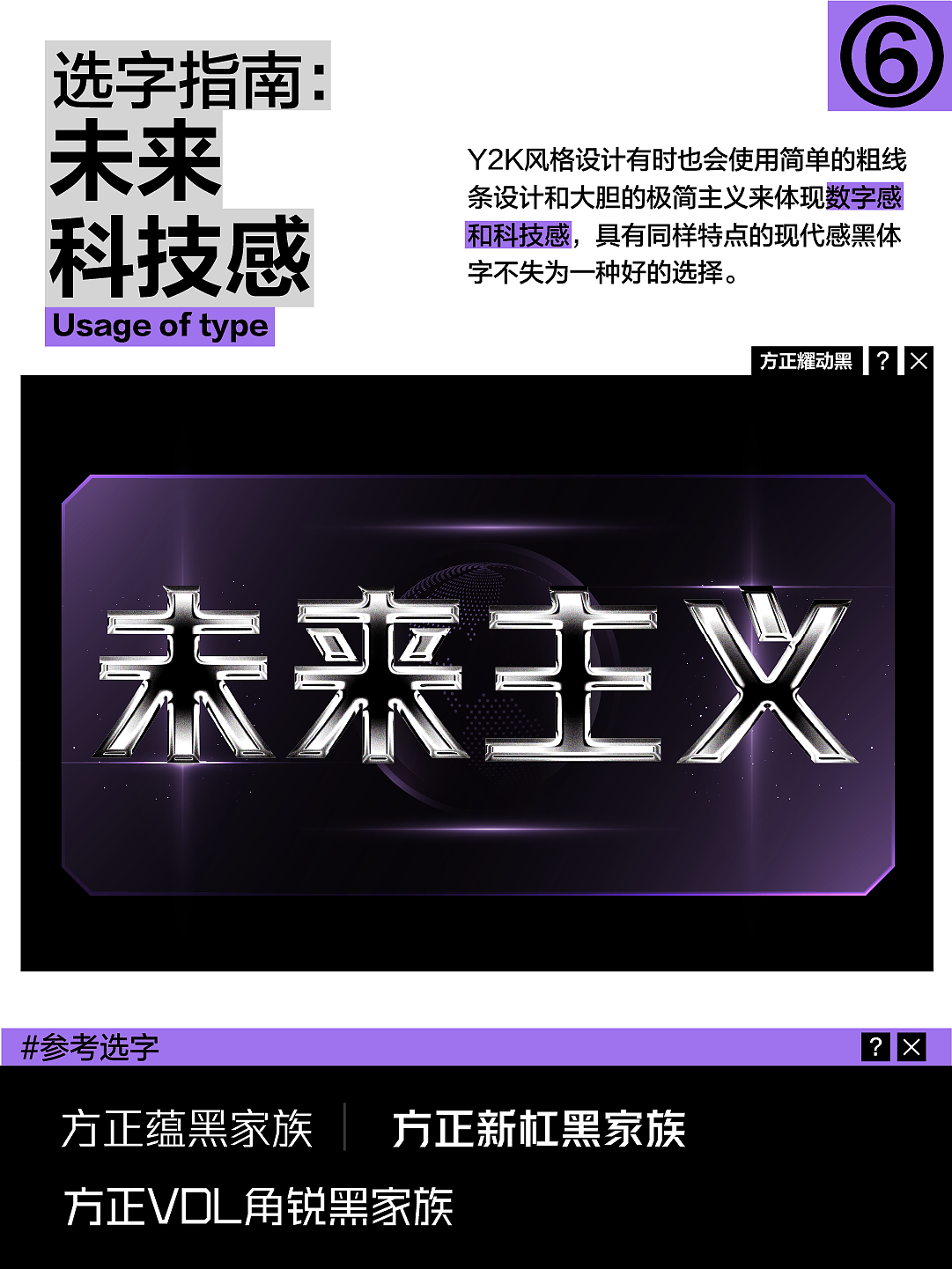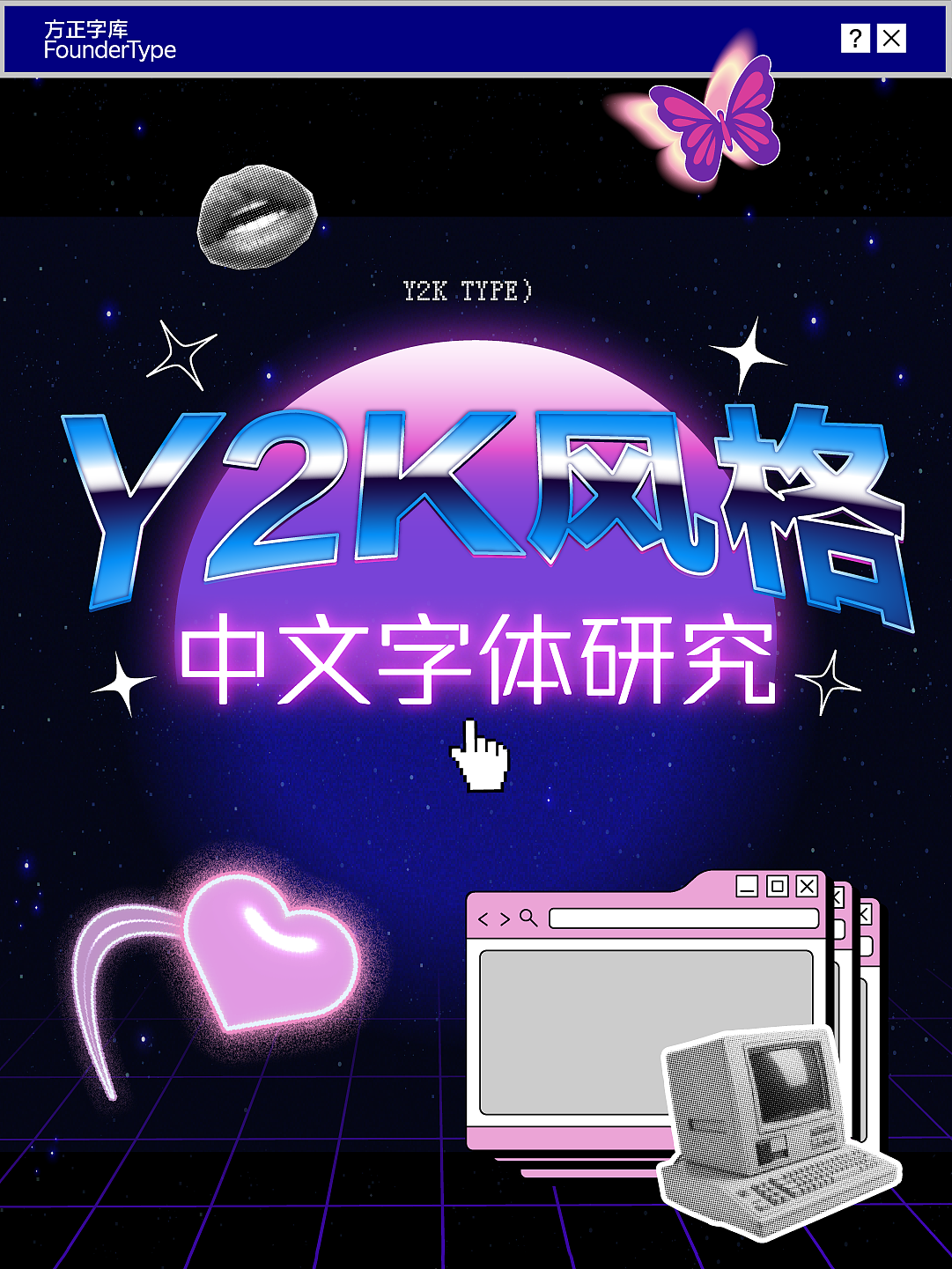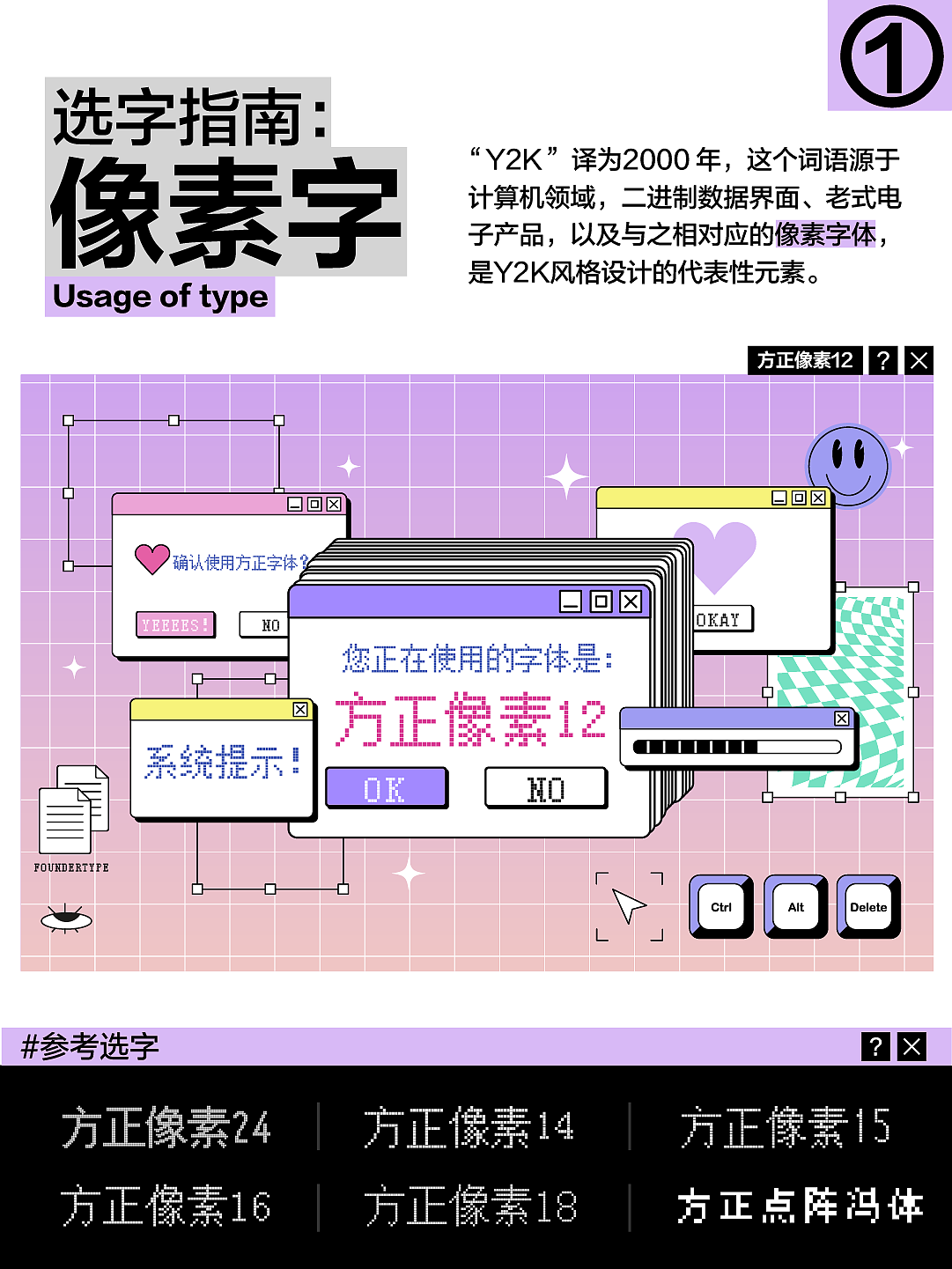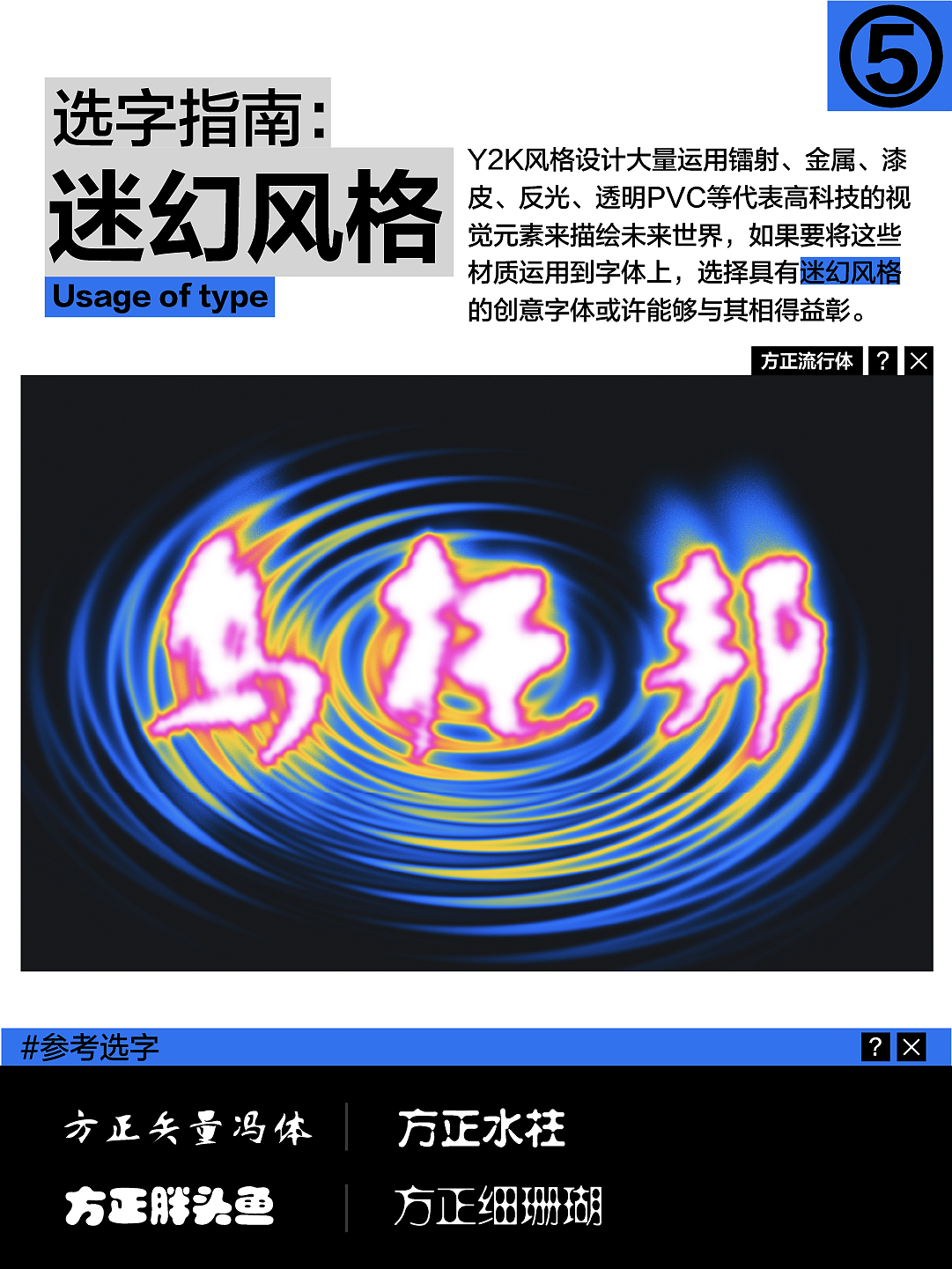
一些中文字体的Y2K美学大赏💅
Y2K风格的诞生,源自千禧年前后人们对未来科技生活的浪漫想象。面对这股爆火的复古风潮,中文字体怎能缺席?我们深入钻研了Y2K风格特性,结合自己的理解,总结了以下贴合Y2K美学的中文字体合集,并进行了设计演绎。下滑查看图片,解锁更适合中国设计师体质的Y2K字体!
👉选“像素字”
在Y2K风格设计中,老式计算机界面以及与之适配的像素字体当属经典。【方正像素家族】原本就是一款用于电子屏幕的功能性字体,家族包含6款字体,其中数字代表最长边的点阵数,适用于LED屏等设备,在现代平面设计中亦可用于表达机械和科技感风格。
👉选“粗体”
线条简洁的粗体字与Y2K风格设计中常用的粗轮廓和大阴影的处理方式相适应。示例中的【方正梯黑】正是这样一款具有稳重力量感兼具几何形态的创意黑体,该字体整体轮廓为正梯形,结构个性鲜明、醒目有力,具有强烈的视觉表现力。
👉选“扁体”
体势扁阔的字体更显力量感,像【方正刚毅体】这样结构整体坚实,笔画粗犷有力的字体也是Y2K风格所偏爱的,配合3D立体和金属质感的设计处理,使得画面张力十足。
👉选“斜体”
自带倾斜角度的字体能够体现画面的运动感和速度感,与Y2K追求前卫的风格相契合。例如【方正风入松家族】,字形自带9度的右上倾斜,提振精神;笔画衔接交叉处的镂空设计则让这款字体白区贯通,更加通透灵动。
👉选“迷幻风格”
具有迷幻风格的创意字体能够与Y2K风格中大量运用的液化流体、镭射金属、漆皮反光等视觉元素相得益彰。例如【方正流行体】以带有流动感的笔触设计而成,笔画间相互融合,流畅舒展富有动感,给人以梦幻的视觉感受。
👉选“未来科技感”
作为代表未来主义的设计风格,具有数字感和科技感的现代黑体是Y2K风格设计最直接的选择。比如【方正耀动黑】,线条简练干净,笔形方圆结合,顶端尖角处理更显字体个性,是一款有着强烈的力量感和震撼的视觉冲击的创意黑体。
👉选“强装饰性”
本身具有强装饰性的字体有时能与Y2K风格设计繁复的画面元素相互映衬。示例中使用的【方正潮流体】,设计灵感源于火车轨道的纵横交错,利用一粗一细的双线表达主笔画,配合单线副笔,营造纵横变化、生机旺盛的氛围,充满时代感和潮流气息。